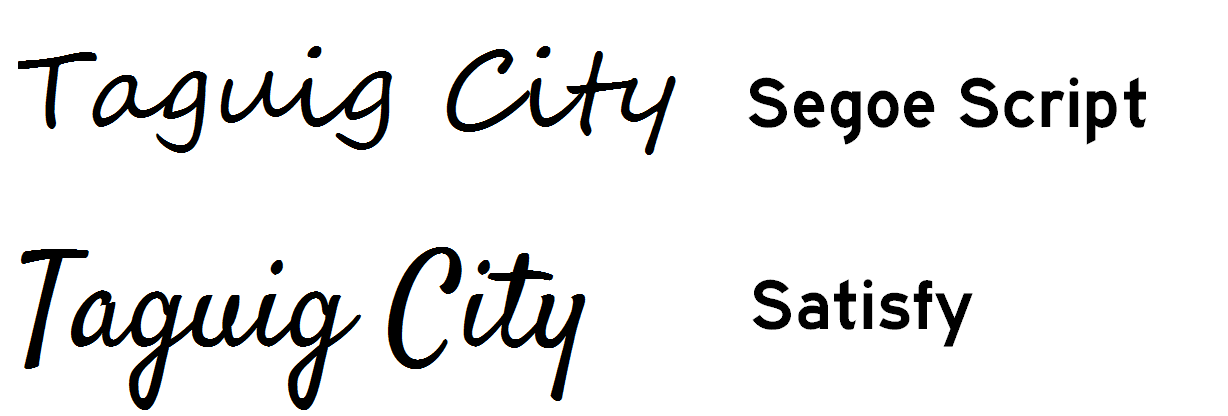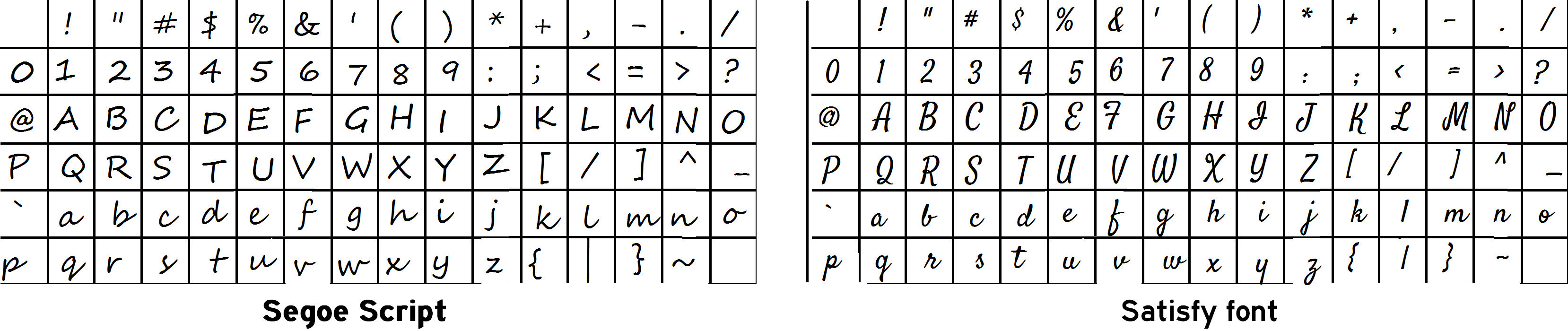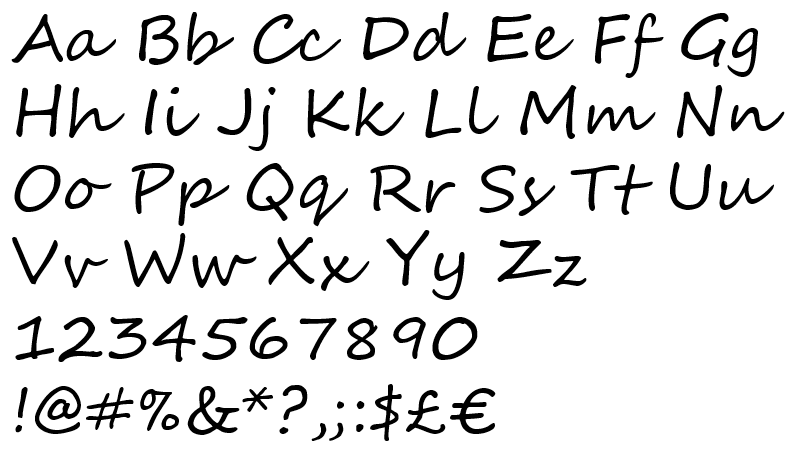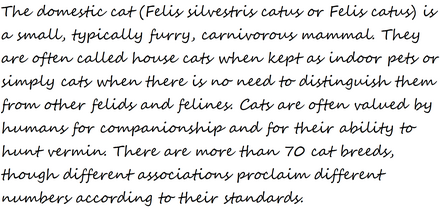
Segoe Script font family — Typography
Segoe Script font is part of the Segoe family of fonts from Microsoft.
Гарнитура, обычно используемая Microsoft
Компания использует Segoe в своих сетевых и печатных маркетинговых материалах, включая недавние логотипы для ряда продуктов. Кроме того, подсемейство шрифтов Segoe UI используется многими приложениями Microsoft и может быть установлено приложениями (такими как Microsoft Office 2007 и Windows Live Messenger 2009 ). Он был принят в качестве шрифта операционной системы Microsoft по умолчанию, начиная с Windows Vista. , а также используется на outlook.com , веб-службе электронной почты Microsoft. В августе 2012 года Microsoft представила свой новый набор корпоративных логотипов в Segoe, заменив логотип, который использовался в течение предыдущих 25 лет.Название Segoe является зарегистрированным товарным знаком Microsoft Corporation, хотя шрифт изначально был разработан Monotype .
История
Segoe был разработан Стивом Маттесоном во время его работы в Agfa Monotype . Лицензия на использование в качестве фирменного шрифта и шрифта пользовательского интерфейса была предоставлена Microsoft для Microsoft.
Лицензионные споры
В 2004 году Microsoft зарегистрировала некоторые шрифты Segoe и Segoe Italic в качестве оригинальных шрифтов в бюро по товарным знакам и дизайну Европейского Союза . Немецкий производитель шрифтов Linotype выразил протест, сославшись на схожесть Segoe UI с лицензированным семейством шрифтов Frutiger . В своем заявлении в ЕС Microsoft утверждала, что Linotype не удалось доказать, что она продавала Frutiger и Frutiger Next до 2004 года.
ЕС отклонил эти претензии, и в феврале 2006 г. ЕС отозвал регистрацию Microsoft. Microsoft не обжаловала это решение. Microsoft по-прежнему владеет патентами США на дизайн различных шрифтов на основе Segoe.
В тот же период, в конце 2004 года, после шести лет правления Agfa Corporation, активы Monotype были приобретены TA Associates, и компания была зарегистрирована как Monotype Imaging .
Позже, в августе 2006 года, компания Monotype Imaging приобрела Linotype. Таким образом, в конце 2006 года Linotype, компания, которая оспорила законность патентов Microsoft на Segoe, стала дочерней компанией, полностью принадлежащей Monotype, компании, которая первоначально предоставила лицензию на Segoe Microsoft.
Некоторые буквы имеют совершенно разные формы в Segoe UI и Frutiger, что отражает различное предполагаемое использование Segoe UI: отображение экрана с низким разрешением, а не вывески аэропорта (Frutiger). Однако Ульрих Штиль утверждает, что многие из этих отличий были введены в более поздних версиях Segoe UI — более ранние версии Segoe UI были ближе к Frutiger.
7 июня 2005 года Scala , компания по производству электронных вывесок (не имеющая отношения к шрифту FF Scala ), объявила, что Segoe удаляется из своего продукта InfoChannel «из-за проблем с лицензированием». Scala заменила Segoe шрифтами Bitstream Vera .![]()
В ноябре 2005 года Саймон Дэниелс, менеджер программы типографической группы Microsoft, заявил, что «оригинальные шрифты Segoe не были созданы для Microsoft или компанией Microsoft. Это был существующий дизайн Monotype, который мы лицензировали, расширили и настроили в соответствии с требованиями различных процессы, приложения и устройства «.
В апреле 2006 года представитель Microsoft по связям с общественностью, попросивший не называть его имени, заявил:
Segoe был оригинальным дизайном, разработанным Agfa Monotype (теперь Monotype Imaging) в 2000 году. В 2003 году мы приобрели оригинальные шрифты Segoe и использовали их для разработки расширенного семейства шрифтов, сохранивших название Segoe. Многие из этих новых шрифтов получили патентную охрану в США. Segoe не произошел от Frutiger. Microsoft также имеет актуальную лицензию, которая позволяет нам распространять определенные шрифты Frutiger в связи с продуктами Microsoft, включая Office и Windows.
Тем не менее, щелкнув стрелку и выбрав «Segoe UI» с помощью мыши, можно.Все новые данные создаются в формате TrueType. Вместе с гигантской языковой поддержкой, широкий диапазон начертаний и курсив с гуманистическим предположением. Я пытаюсь использовать на своей веб-странице шрифт Segoe Print, который не является шрифтом браузера по умолчанию. Шрифт Segoe Print просмотрен 15744 раза и скачан 14942 раз. Окна や Mac に OS 標準 で 入 っ て い る と 思 わ れ る フ ォ ン ト, Microsoft Office や Adobe 製品, DynaFont な ど に 添 付 さ れ て い る フ ォ ン ト の リ ス ト で す. フ ォ ン ト が イ ン ス ト ー ル し て あ れ ば, 任意 の テ キ ス ト を 各 フ ォ ン ト で シ ミ ュ レ ー シ ョ ン し、 実 際 の 表示 を 確認 で き ま す。 На Fontsup можно найти более 79364 других обычных шрифта.Уведомление о файлах cookie. Продолжайте читать, чтобы узнать, как использовать кнопки слева. Этот шрифт был опубликован 8 мая 2015 года и называется « Segoe Script является частью Segoe of. И при нажатии кнопки Ctrl шрифт приобретает свою идентичность в рамках типографской записи! Свободно доступные шрифты для Windows, Linux и Mac отображаются в меню шрифтов на всех! Просмотрите прикрепленные сюда изображения и получите представление о том, насколько бесплатный шрифт Script для ПК / Mac.